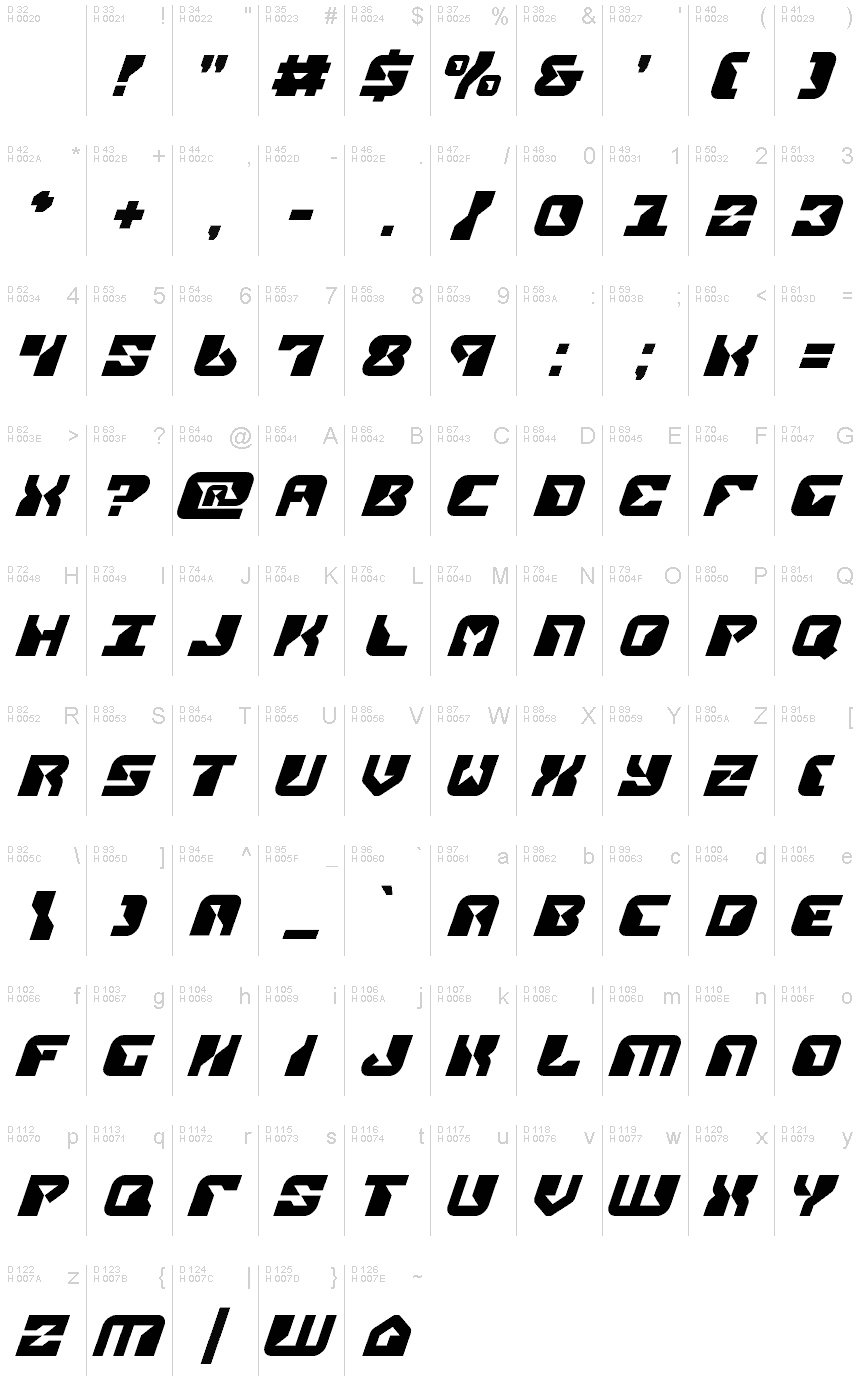
Replicant Italic od Iconian Fonts to darmowy font typu techno display o ostrym, cyberpunkowym charakterze. Wielkie litery sprawiają wrażenie wyciętych z czarnych płyt – twarde, ukośne cięcia i trójkątne wcięcia nadają im szybki, syntetyczny rytm, całkowicie odmienny od gładkiego przepływu tradycyjnej kursywy.
Naturalnie wpasowuje się w plakaty sci-fi, logotypy gier, grafiki streamingowe, okładki albumów i plansze tytułowe, wszędzie tam, gdzie darmowy font musi od razu budować futurystyczny klimat. Dzięki pochyleniu liter i ostrym, kanciastym wycięciom sprawdzi się również w krótkich nagłówkach, brandingach w stylu interfejsu oraz monogramach, które mają emanować chłodną, technologiczną precyzją.